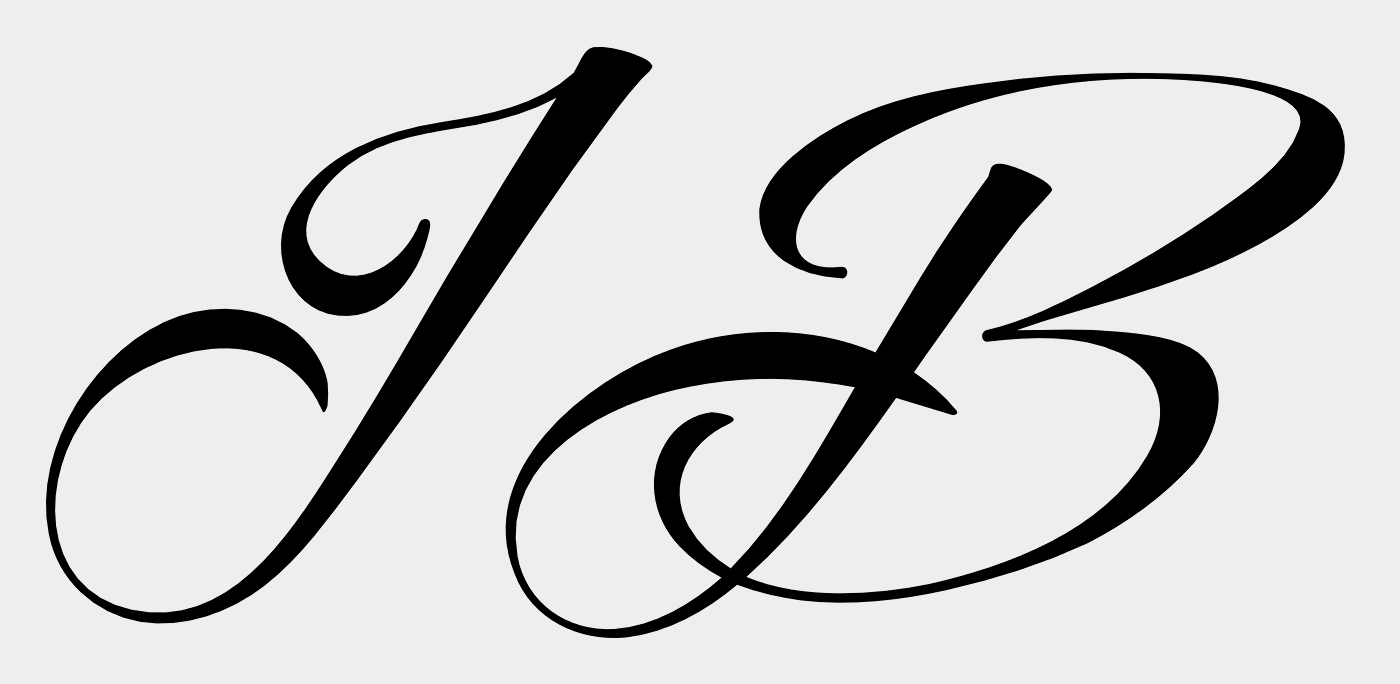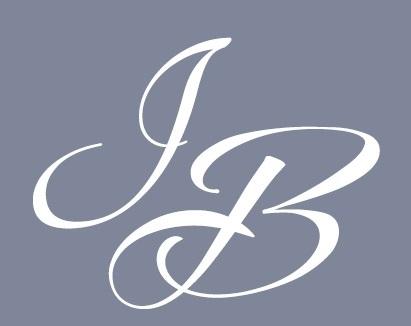
Wer kann diese Logo Schriftart identifizieren? (Initialen)
wir haben ein älteres Firmenlogo, welches wir gerne weiter überarbeiten möchten. Leider gibt es den damaligen Webdesigner nicht mehr und es gibt keinen Hinweis darauf, um welche Schriftart es sich handelt. Wir haben das Logo auf sämtlicher Arbeitskleidung, Maschinen usw. und wollen das Logo ergänzen, die Schriftart soll aber die gleiche bleiben, da unser Logo bei Geschäftspartner überall bekannt ist. Kann uns jemand weiterhelfen .... oder hat einen Hinweis??? Freue mich über Hinweise und Antworten!
Das B ist aus der Reditum, das J hab ich dort auch in den Glyphen nicht gefunden …
… und das J ist aus der Tangerine Bold.
Echt mal! Daran hatte ich mir auch die Zähne ausgebissen. Kann die Schrifterkennungs-AI mit solch geschwungenen Schriften überhaupt umgehen? http://www.whatfontis.com/ wollte an diesem schnell hingeschuppsten Muster nicht mal erkennen, dass dort überhaupt zwei Zeichen standen, geschweige denn welche …
Vor allem wäre ich nicht darauf gekommen, dass 2 verschiedene Schriftarten benutzt wurden.